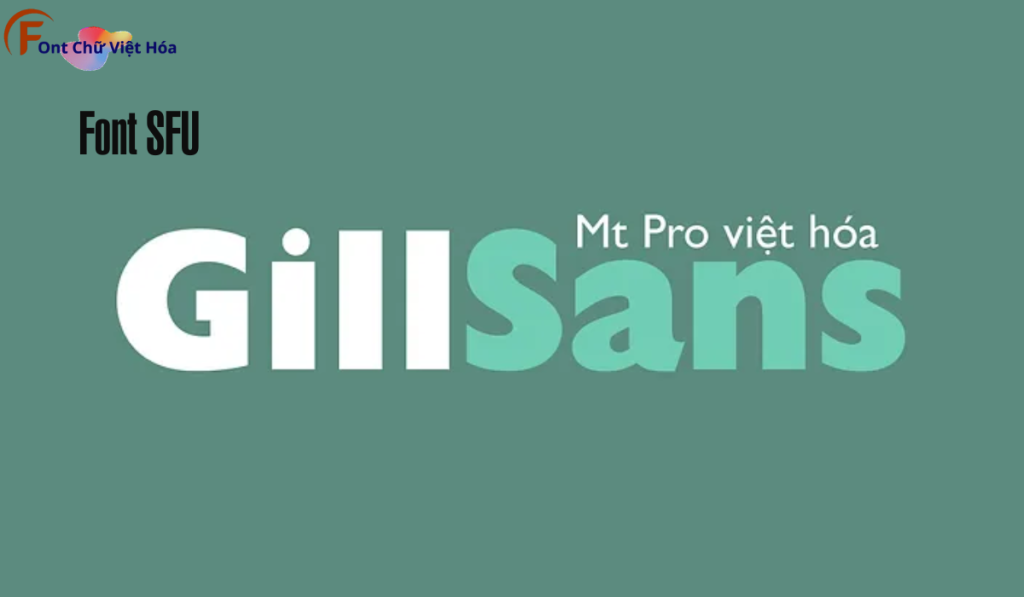
Font Chu SFU Gill San Mt Việt Hóa
Tác giả: Eric Gill
Bộ Font: SFU
Độ dày: Regular, Bold, Italic
Font Chu SFU Gill San Mt Việt Hóa, thuộc bộ font SFU, là biểu tượng của sự thanh thoát và tinh tế với phong cách sans-serif hiện đại. Font này được thiết kế nhằm mục tiêu tạo ra sự rõ ràng và dễ đọc, đặc biệt phù hợp cho các thiết kế như poster, logo, và tiêu đề. Đặc điểm hình dạng của SFU Gill San Mt là các đường nét sắc sảo và tỷ lệ chữ cân đối, giúp tối ưu hóa không gian và tạo ấn tượng thị giác mạnh mẽ. Font này cũng đã được Việt hóa, mang đến sự linh hoạt và tiện dụng cho các dự án thiết kế bằng tiếng Việt, giúp người dùng dễ dàng tiếp cận và sử dụng.